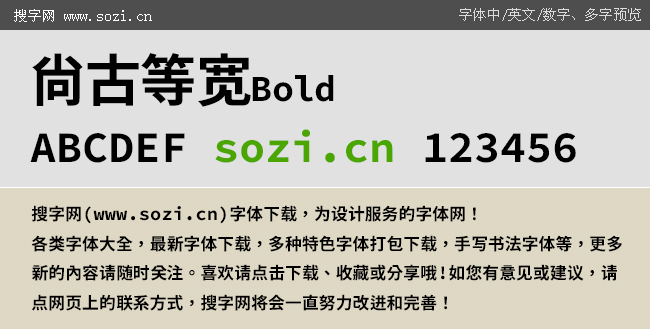
尚谷等寬Bold
搜字網提供一款尚谷等寬Bold中文字體下載,尚古字體是一套泛中日韓傳承字形(舊字形),基于思源黑體、思源宋體、思源等寬以及思源系列衍生字型制作,包含黑體、明體、圓體、等寬以及簡轉繁字型。這款字體無論是個人還是企業都可以自由免費商用,無需知會或者標明原作者。適合包裝設計、海報設計、廣告設計等應用。